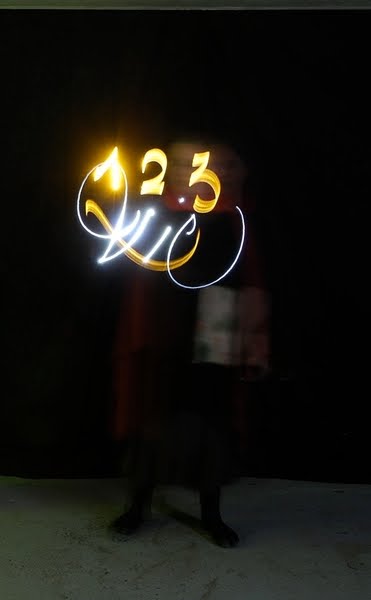
Quelques démonstrations de Julien Breton :
Les 6 et 7 mars 2010, je suis allée à Nantes suivre un stage animé par Julien Breton : Calligraphie arabisante et initiation au lightgraff. Je vous ai déjà entretenus de la partie Calligraphie arabisante. (Post du mercredi 10 mars). Je vous présente maintenant la partie lightgraff.
Après avoir travaillé les lettres arabisantes de Julien, nous avons passé la dernière après-midi à nous initier au lightgraff. Beaucoup de rires.
Le principe dans un espace intérieur : dans une pièce noire, sur un fond noir, on manipule des lampes variées devant l'objectif d'un appareil photo réglé pour prendre des photos dans le noir. Il faut un appareil numérique qui puisse rester ouvert plus de 30 secondes. Cela correspond à la "pause B" des appareils argentiques qui autrefois permettaient par exemple de prendre des photos de feux d'artifices. On déplace des sources lumineuses (néon, lampes de poches, petites lampes à faisceau...) autoalimentées (pas de problème de fil) devant l'objectif. Plus l'exposition lumineuse est lente, longue, plus les traces lumineuses gagnent en intensité. Les néons donnent des traces larges, les petites lampes à faisceau des traits fins, des caches sur les lampes de poche des traits moyens. Le principe des tracés est le même que celui des outils calligraphiques carrés.
Cependant, obtenir de beaux résultats suppose de dépasser deux difficultés importantes : en premier lieu, tracer dans le vide, avec très peu de repères ; en second écrire à l'envers, sans décaler les points de jonction des différents traits.
Julien commence par mettre sa composition au point sur papier, puis il s'entraîne à en reproduire la chorégraphie dans l'espace. L'enchaînement de ses lents mouvements ressemble à une danse.
Pour nous stagiaires, il s'agissait de découvrir le principe, d'essayer. Et cela s'est fait , comme vous pouvez le constater, de manière très ludique.
Le modeste résultat auquel je suis arrivée.
Carnet de recherche : 1. Tire-ligne et empreintes.
L'année dernière, lors d'un stage "Cuisine et Techniques" animé par Yveline Abernot, j'ai réalisé plusieurs carnets de recherches. Je vous en ai déjà présenté un : "Fonds structurés". Celui que je vous montre aujourd'hui répond en fait à deux propositions de recherche : En premier lieu rechercher des possibilités non explorées d'un outil calligraphique - ici un Tire-ligne de Jonh Neal - et en second, les possibilités plastiques d'une lame de microscope en verre. Dans les deux cas, j'ai utilisé du papier léger chinois Wenzhou et du papier dessin grain léger (200g) de Sennelier. J'ai choisi de travailler dans l'humide, voire le mouillé, très mouillé. Il y avait un évier à proximité.
Dimensions du carnet fermé : 16x24 / Reliure cousue à la japonaise.
1. Tire-ligne et empreintes.
Opérations réalisées :
-Pose de traits courts sur feuilles de papier dessin à la gouache Linel noire.
-Prise d'empreinte avec du papier dessin.
-Prise d'empreinte avec du papier chinois.
-Lavage partiel sous le robinet et contrôle du déplacement de la couleur par balancement.
-Passage d'eau entre le papier chinois et le papier dessin.
-Imprégnation préalable de zones délimitées à l'eau claire et au pinceau avant la prise d'empreintes.
-Transferts successifs.
Regarder le diaporama
Explications de la seconde recherche à suivre.
Les outils de l'anglaise
La pratique de l'anglaise s'appuie sur un entretien régulier, des gammes.
En voici les outils : une plume baïonnette, un flacon d'encre ferrique et pour le plaisir, une feuille d'Arches satin.
Un extrait de mon carnet de fonds de matières qui s'est transformé en carnet de fonds et d'essais. Sur cette page, un essai réalisé avec un parallel pen usiné. Les traits épais sont scratchés et les contours et liaisons des lettres redessinés rapidement à la pointe de l'outil. Médium : brou de noix.